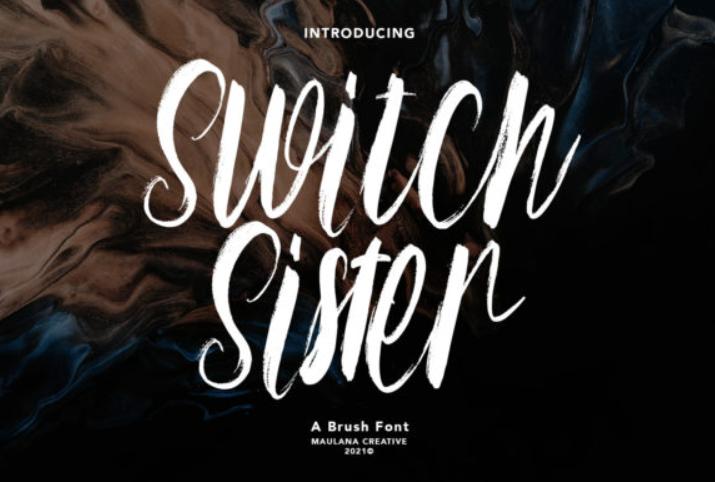
[Creativefabrica] Switch Sister Font (Maulana Creative)
Switch Sister - прекрасный начищенный шрифт с очаровательными игривыми персонажами, которые, кажется, танцуют вдоль базовой линии. Добавьте этот шрифт к своим самым креативным идеям и обратите внимание, как они выделяются среди них!